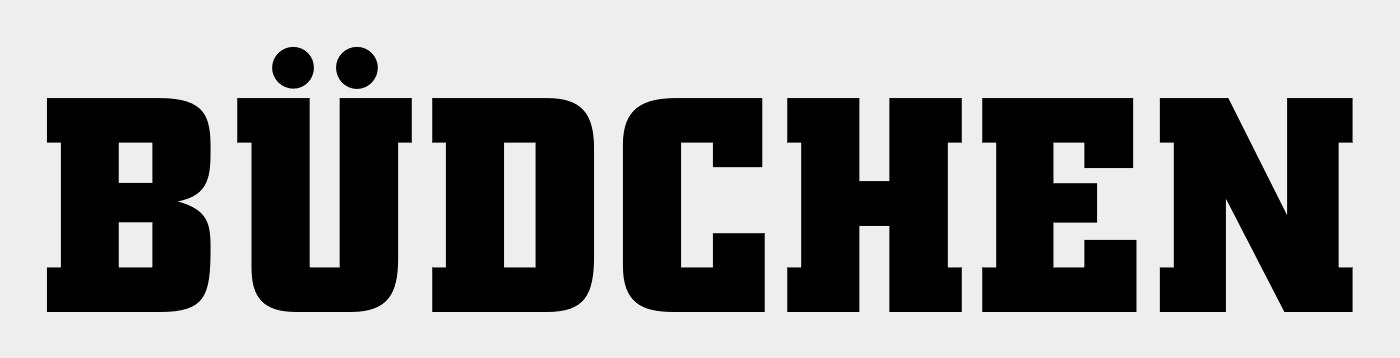
Suche Schriftart von Borussia Dortund
Hallo. Ich bin auf der Suche nach einer Schriftart die im Stadion in  Dortmund am Büdchen vor der Südtribüne dran ist. Kann mir jemand helfen welche Schriftart das ist? Also die in der "Büdchen" geschrieben ist? Danke :-)
City Pro Bold (Berthold) -> bei myfonts suchen.
das erinnert mich an die City BQ.
Typeface: City BQ
Designer: Georg Trump
Year: 1930
Publisher: Berthold (H. Berthold AG)
Aber von der gibt es keine Outline oder ähnliches. Hat da Jemand an die City BQ Hand angelegt? Die verringerte Strichdicke im verkleinerten Ü deutet IMHO auf Handarbeit hin.